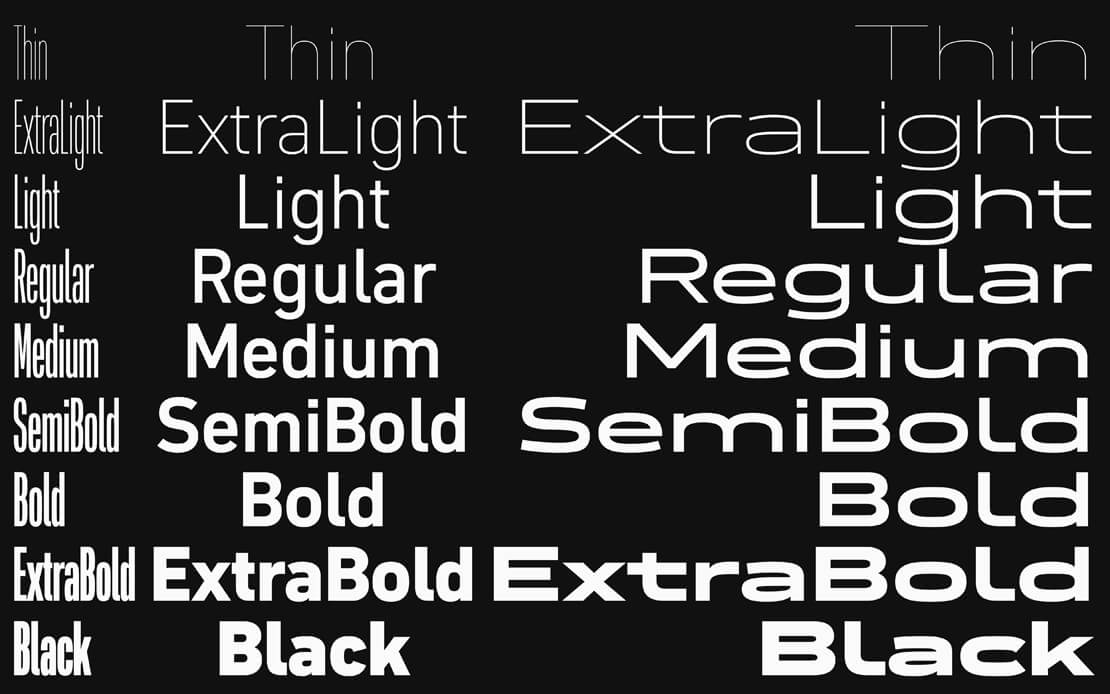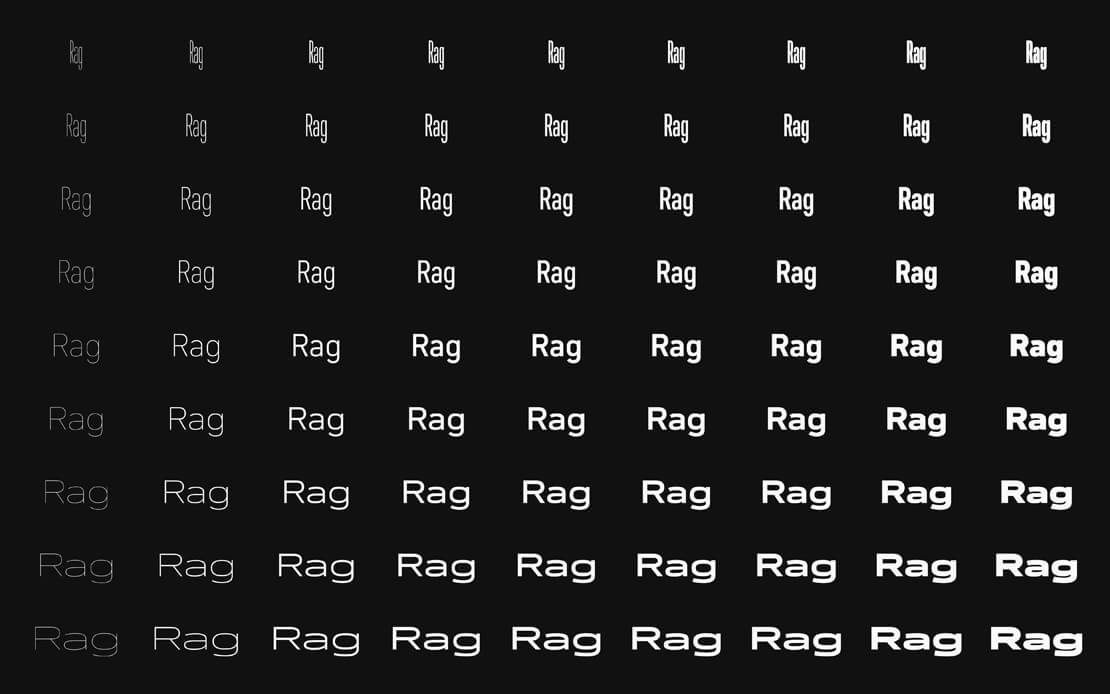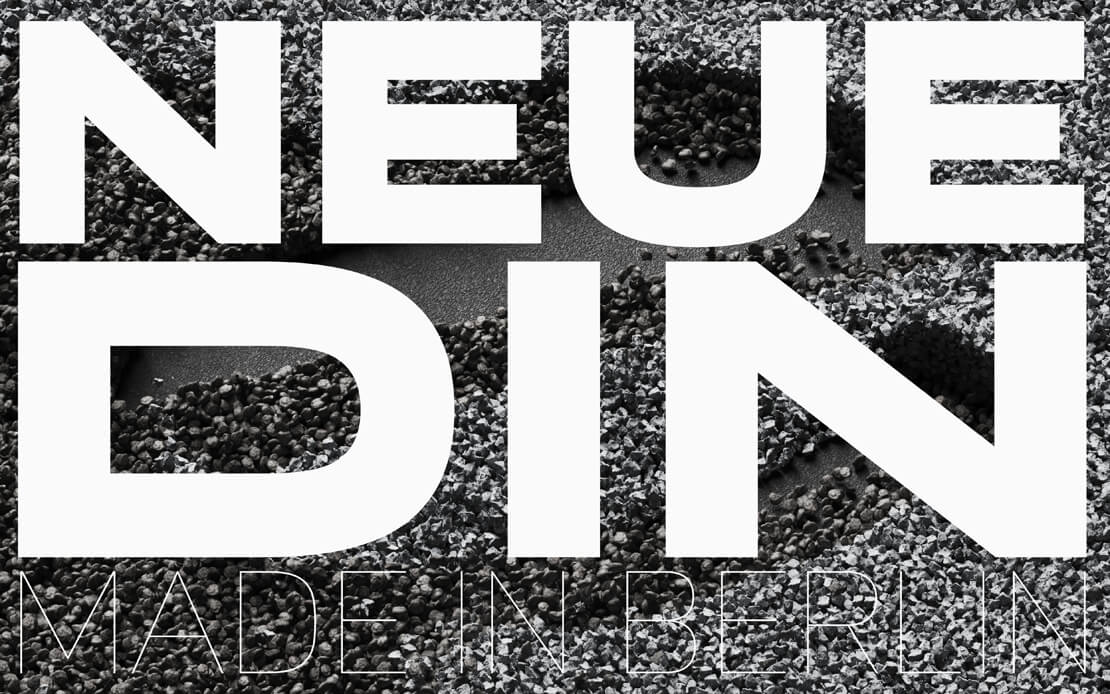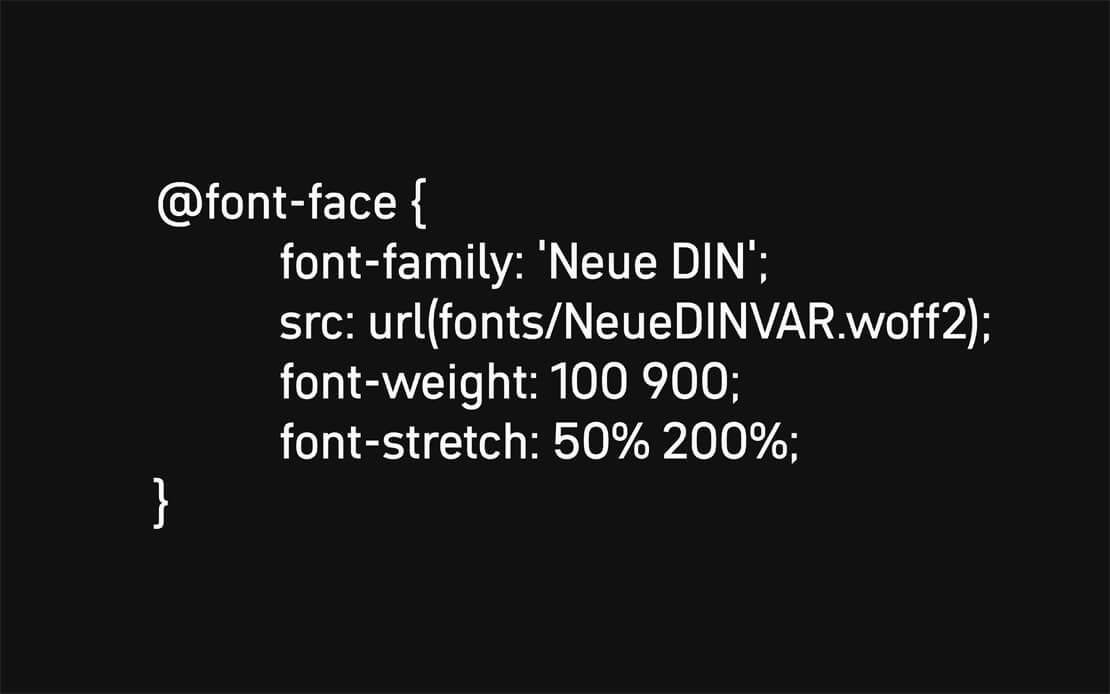
Neue DIN – made in Berlin
Hendrik Weber, Andreas Frohloff und Olli Meier haben die DIN-Schrift neu interpretiert. Die variable Schriftart »Neue DIN« vereint fließend sehr schmale und extreme breite Schnitte und ist neu bei Fontwerk erschienen.
Die DIN kann man mittlerweile als eine echte deutsche Schriftikone bezeichnen. Mit ihrem neuen Schriftprojekt haben sich die drei Typedesigner zwar am ursprünglichen Design des frühen 20. Jahrhunderts orientiert, die Neue DIN wurde jedoch komplett neu konzipiert und gestaltet.
Wie schon vor 100 Jahren, ist auch die Neue DIN zu 100% in Berlin entstanden. Bei der neuzeitlichen Umsetzung standen allerdings die Anforderungen der digitalen Zeit im Fokus. So ist schließlich eine elegante Schrift entstanden, die einen fließenden Übergang von »Condensed Thin« bis »Wide Black« ermöglicht und darüber hinaus weitere OpenType-Features bietet.
Auf der entsprechenden Microsite lässt sich mit dem Variable Font experimentieren und die insgesamt 81 Schnitte in Aktion erleben. (Tipp: Maus in der Desktop-Fassung bewegen oder in der mobilen Version die Bildschirmausrichtung aktivieren.)
»Unser brandneuer Release erweitert mit seiner Detailvielfalt und lang ersehnten Flexibilität die Palette der DIN-Schriften um eine wichtige neue Variante«, so Ivo Gabrowitsch, Gründer von Fontwerk. »Dank des Zusammenspiels von Design und moderner Technologie hat sich die Neue DIN zu einer Schrift entwickelt, die mit der Zeit geht und den perfekten Standard für die Bewältigung der Anforderungen von heute setzt.«